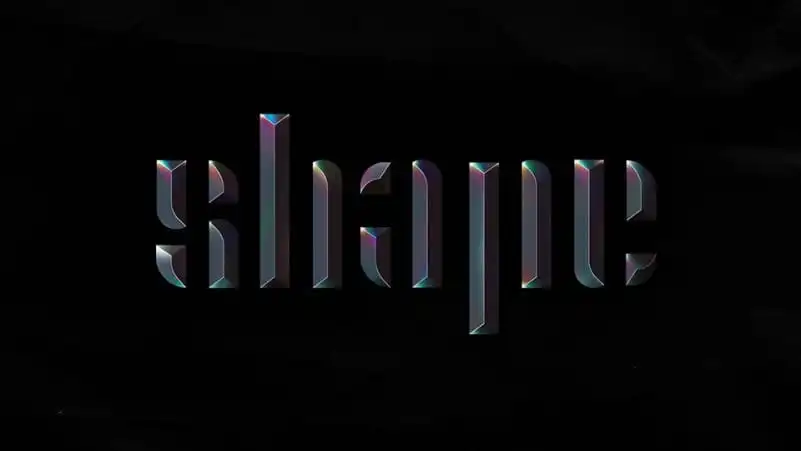
A Shape Display Font é uma elegante e moderna escolha para quem deseja dar um toque especial ao seu projeto visual. Inspirada em linhas aguçadas e extremidades projetadas, esta font criativa adota um estilo neo-futurista. Perfeita para criações de impacto, como o design do logotipo ou a composição de letras no site da sua empresa, ela adicionará sofisticação e estilo ao seu trabalho. Com uma aparência que remete à natureza moderna e à tecnologia avançada, esta fonte traz um toque único aos seus projetos. Perfeito para anúncios, identidades corporativas e materiais gráficos promocionais, ela é ideal tanto para os profissionais de design como para designers amadores que buscam dar vida a seu trabalho criativo com uma estética contemporânea. A Shape Display Font não apenas oferece um estilo único para suas criações digitais, mas também adiciona sofisticação e distinção ao seu material visual. Este é um excelente escolha para quem procura um recurso gráfico que seja à medida do seu projeto, destacando-se no meio de uma gama diversificada de fontes disponíveis no mercado atualmente.